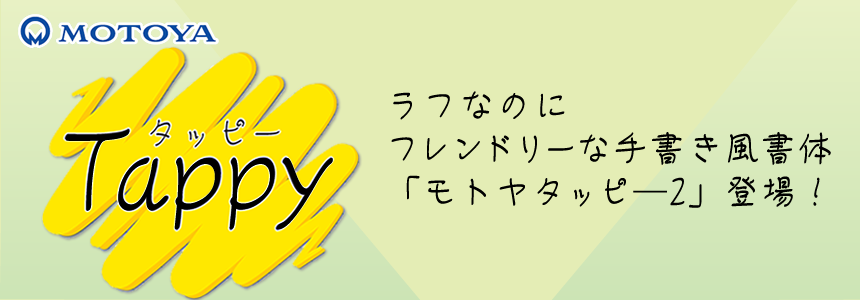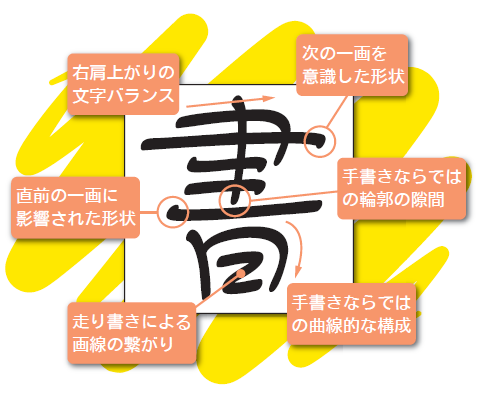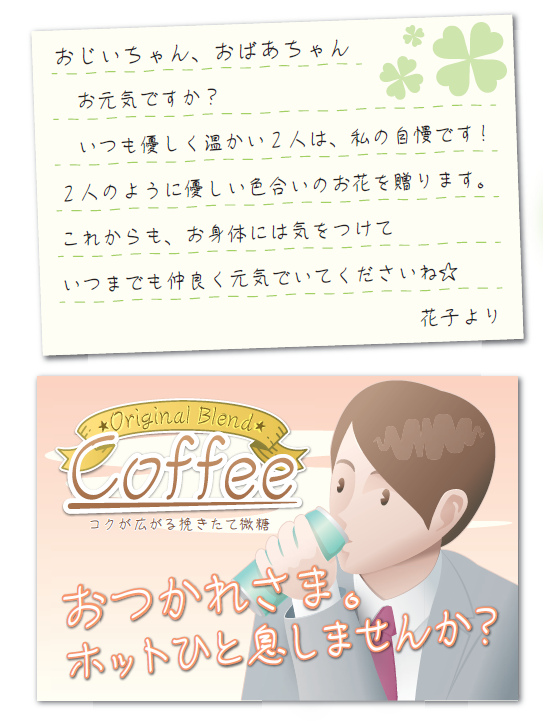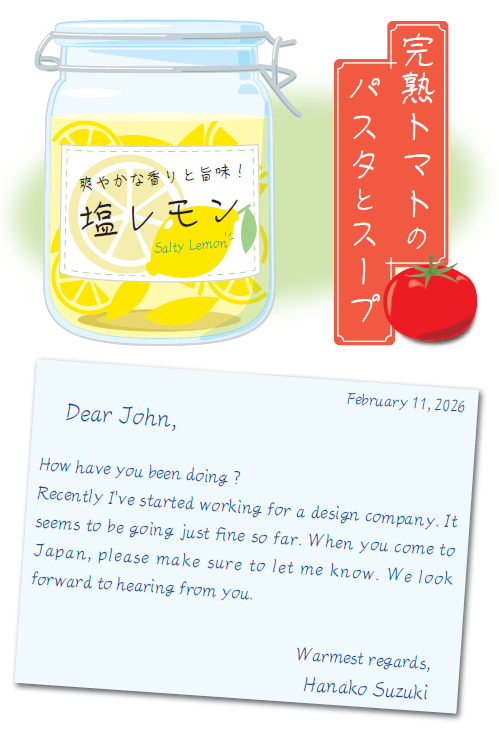
モトヤ新書体「モトヤタッピー2」
この度、モトヤよりラフなのにフレンドリーな手書き書体「モトヤタッピ―(Tappy)2」をご紹介!
■書体見本
■モトヤタッピ―のコンセプト
| モトヤタッピ―は、ボールペンなどで少し急いで書いたような、書き崩れた文字が特徴の手書き風書体です。 制作においては、クラスメイトから借りた授業ノートに書かれていそうな「ラフだけど親しみやすい」「上手すぎず、下手すぎない」「整っていないけど読める」、そんな身近な文字を目指しました。 書体名は、「下手(へた)っぴ」でもあり「達筆(たっぴつ)でもあることから「タッピ―」と名付けられました。 | ![]() |
■書体見本・使用例
モトヤタッピ―は親しみやすい表情を持っているので、誰かへ宛てたメッセージへの使用はもちろん、例えば学園生活をテーマにしたような映画やドラマ、アニメ作品とも相性が良く、広告媒体ではテレビCM、食品・飲料のパッケ―ジなどでも使用しやすく、それを見た人が親近感を覚えるような、人に寄り添う表現ができます。